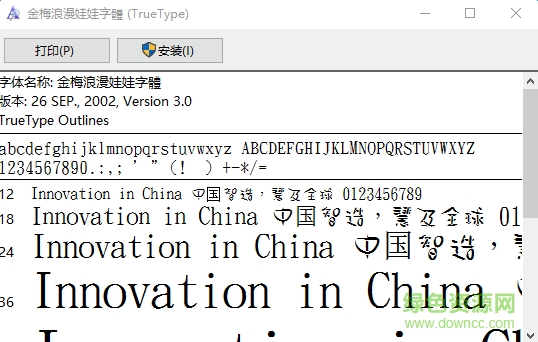
金梅浪漫娃娃
金梅浪漫娃娃字體是一款很有個(gè)性的電腦字體,這款字體不像普通字體那樣呆板,它是很活潑的,而且就像它的名字所說(shuō)是有浪漫的元素的,所以寫出來(lái)的字也是很好看的,歡迎大家來(lái)綠色資源網(wǎng)下載。
金梅浪漫娃娃這款字體是很實(shí)用的,大家可以用來(lái)寫作、或者是藝術(shù)設(shè)計(jì),因?yàn)閷懗鰜?lái)的字好看,所以也有很多人喜歡,不知道大家是否也喜歡呢。